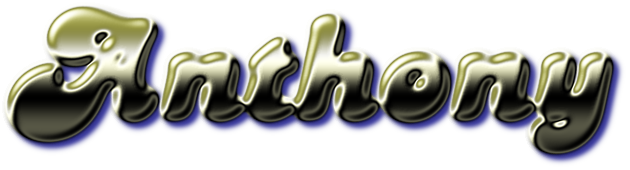
より複雑なフォント, ネオンサイン, メタリック 文字の描画は ImageMagick でできることの始まりにすぎません。ここでは IM の基本的な文字描画機能を修正して、凝ったフォントや特殊効果を作る方法を見ていきます。それらは Web ページや文書で使うことができます。
複合フォント効果
画像としての単なる文字は退屈ですが、ほんの少しの手間で文字を重ね合わせて色付けすれば、とても奇妙で素晴らしい効果を生み出せます。これを行うには、文字を複数回描画し、異なるタイルや色を重ね、利用可能な数多くの画像演算子を適用して、元の退屈な文字からより興味深い特殊効果を生成する必要があります。これらの効果の多くは、ここで使っているような基本的なフォント以外の画像にも適用できることに注意してください。特にクリップアート画像に効果を使うことができます。 タイルフォント : フォントを固定色で描く必要はありません。フォントの上にタイルパターンを使えます。
「-tile」設定は、「-draw」演算子に対する「-fill」色をすべて上書きすることに注意してください。 |
IM v6.3.2 以降では、代わりに「-fill」設定でタイル画像を指定できます。ただしこの使い方は推奨されません。なぜなら「-fill」色を使う多くの演算子がタイル画像を理解できず、代わりに 'black' を使ってしまうからです。 |
タイル画像は、「-tile」画像を設定する前に「-origin」設定を指定することで、背景画像の原点に対してオフセットできます。画像は塗りタイルとして割り当てられる際に、指定した量だけロールされます。 グラデーションフォント : 使用するタイルは小さい必要もなく、キャンバス全体の大きさにできます。 |
ハードシャドウ : フォントをオフセットを付けて2回描画することで、単純な「ハード」な影効果を作れます。
傾けた影 : 「-annotate」フォント描画演算子は、垂直方向と水平方向を別々に回転できるため、フォントに変わった回転「傾斜(slewing)」や「せん断(shearing)」を指定できます。これは奇妙な影を作ったり、独自のイタリックや斜体フォントを作るのに最適です。
文字回転の効果をまとめた表は、Annotate テキストオプションを参照してください。もちろん Candice フォントはこの効果を示すのに良いフォントではなく、結果をより3Dらしく見せるには別の細工が必要かもしれません。例えば距離で影をぼかすなどです。 斜体フォント : 「-draw」を使ってフォントを斜めにすることもできますが、描画面を歪ませるために追加の MVG (Magick Vector Graphics) 操作が必要になるため、少し難しくなります。描画面を歪ませるので、歪ませる前に 'translate' を使ってフォントの位置を先に設定するのが良い考えです。
| 文字回転の効果をまとめた表は、Annotate テキストオプションを参照してください。もちろん Candice フォントはこの効果を示すのに良いフォントではなく、結果をより3Dらしく見せるには別の細工が必要かもしれません。何か面白いものを思いついたら、私に教えてください。世界中の他の人々と共有できるように。 | 「-annotate」と「-draw skew?」操作は、実際には描画面の X 軸と Y 軸を回転させます。これは既存の画像に「-shear」を使う効果とは異なります。「-shear」は画像のせん断された軸を伸ばすため、操作によって画像の高さ(または幅)が変わることはありません。 |
| スタンプフォント : フォントをより暗い色、より明るい色、そして元の色で3回描画することで、スタンプのようなくぼみを作れます。 |
フォントの最後の 'draw' が、フォントの中央部分を消していることに注目してください。これは単色の背景でのみ可能です。単色でないランダムな背景でこれをどう使うかはマスク画像の使用を参照してください。2つの色を入れ替えると、もちろんくぼんだフォントではなく、盛り上がったフォントが得られます。 押し出し または 3D ブロックフォント: フォントを複数回繰り返すことで生成できます。
これは単なる影ではなく、描画されたフォントの適切な厚みづけであることに注意してください。これは非常に反復的で、あらゆる「形状を持つ」画像に使えます。この別の例についてはサムネイルに厚みを加えるを参照してください。
アウトラインフォント : 小さな位置オフセットを付けて複数回描画することで、アウトラインフォントを作れます。
これも非常に反復的なので、良いアウトライン手法ではありません。ImageMagick では「-stroke」設定を使ってフォントのアウトラインを描けるため、はるかに良い手法が存在します(後述のストロークフォントを参照)。とはいえ、このような複数回の再描画によるアウトライン生成は、インターネット上のいたるところで見つかる既製のクリップアート画像に対しては非常に便利です。また「-stroke」設定が使えない他のグラフィックライブラリやプログラム(「PHP」の「GD」など)でも便利な手法です。このアウトライン手法を示すもう一つの理由は、非常に尖った点を持つフォントのアウトラインを描く場合に、結果がより良くなることがあるからです。例えばここでは、フォントの尖った点を際立たせるためにフォントを12回描画しています。ここでのアウトラインも少し太く描かれています。